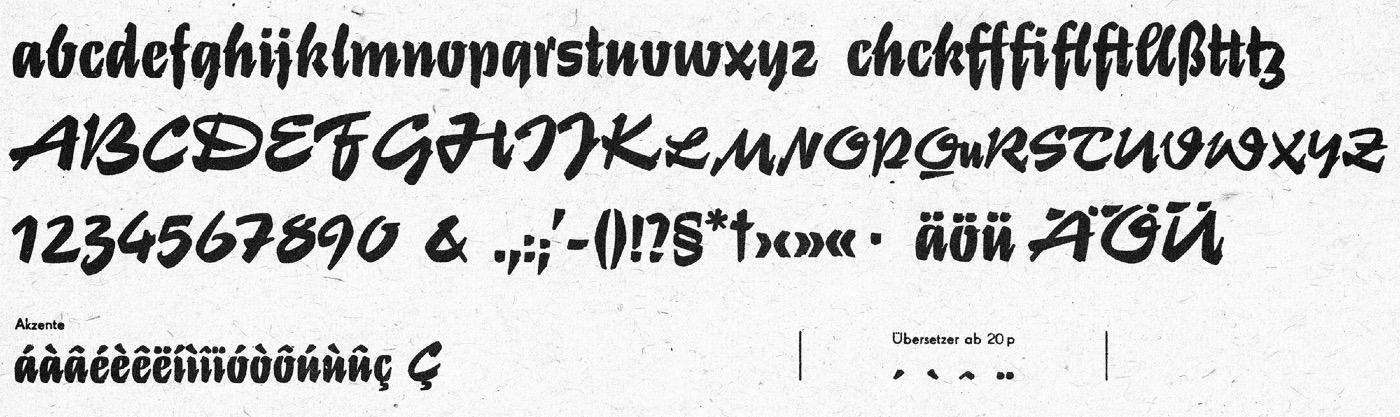
Font-Wiki: Stentor
• 1964
• Antiqua dekorativ
Die unverbundene Pinselschreibschrift Stentor von Heinz Schumann erschien 1964 beim DDR-Schrifthersteller Typoart. Es gibt zahlreiche Digitalisierungen der Schrift: unter dem Originalnamen bei URW++, Scangraphic und Elsner+Flake sowie als Rosalia von preussType und Tyton Pro von RMU Fonts.
Original-Bleisatzmuster von Typoart